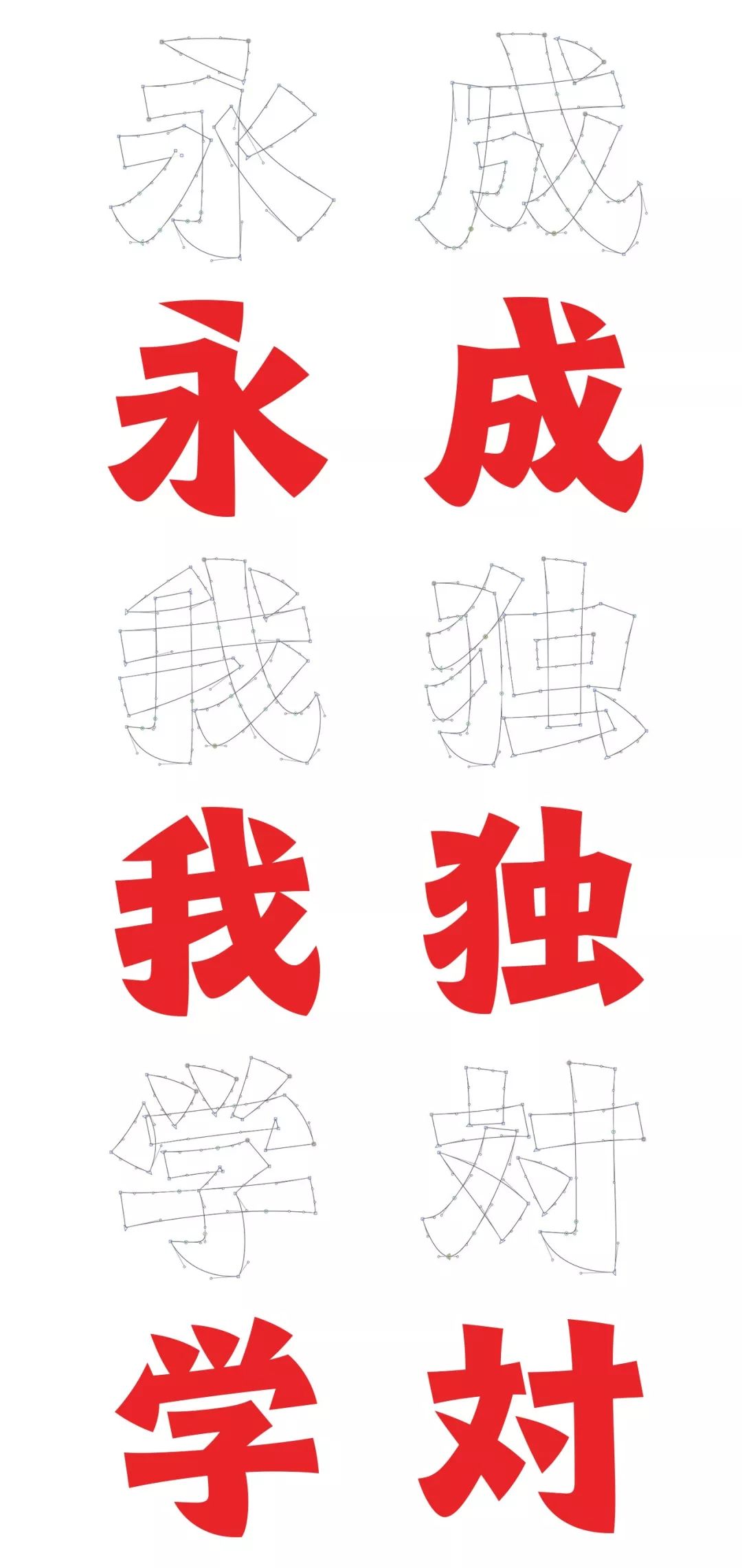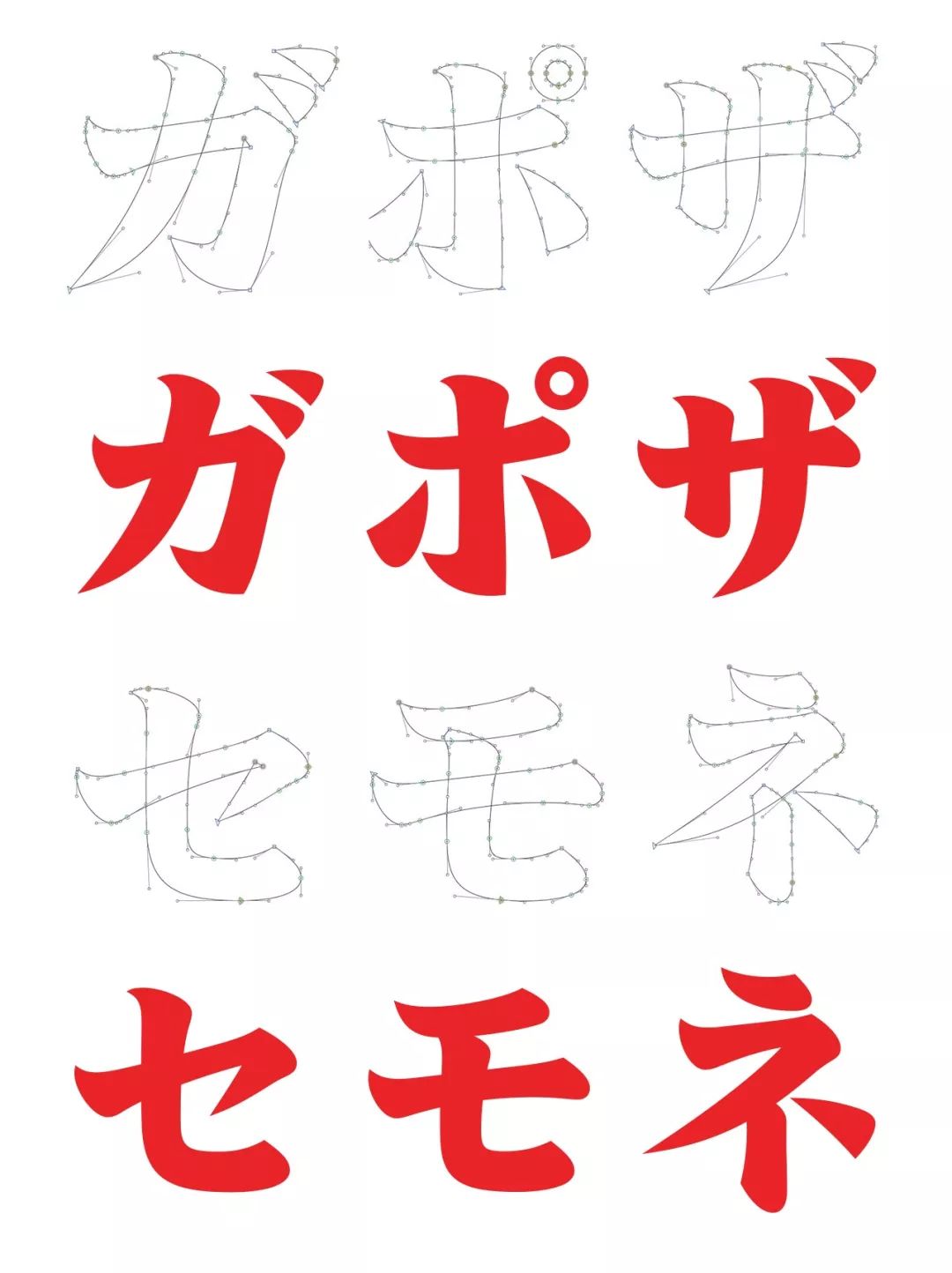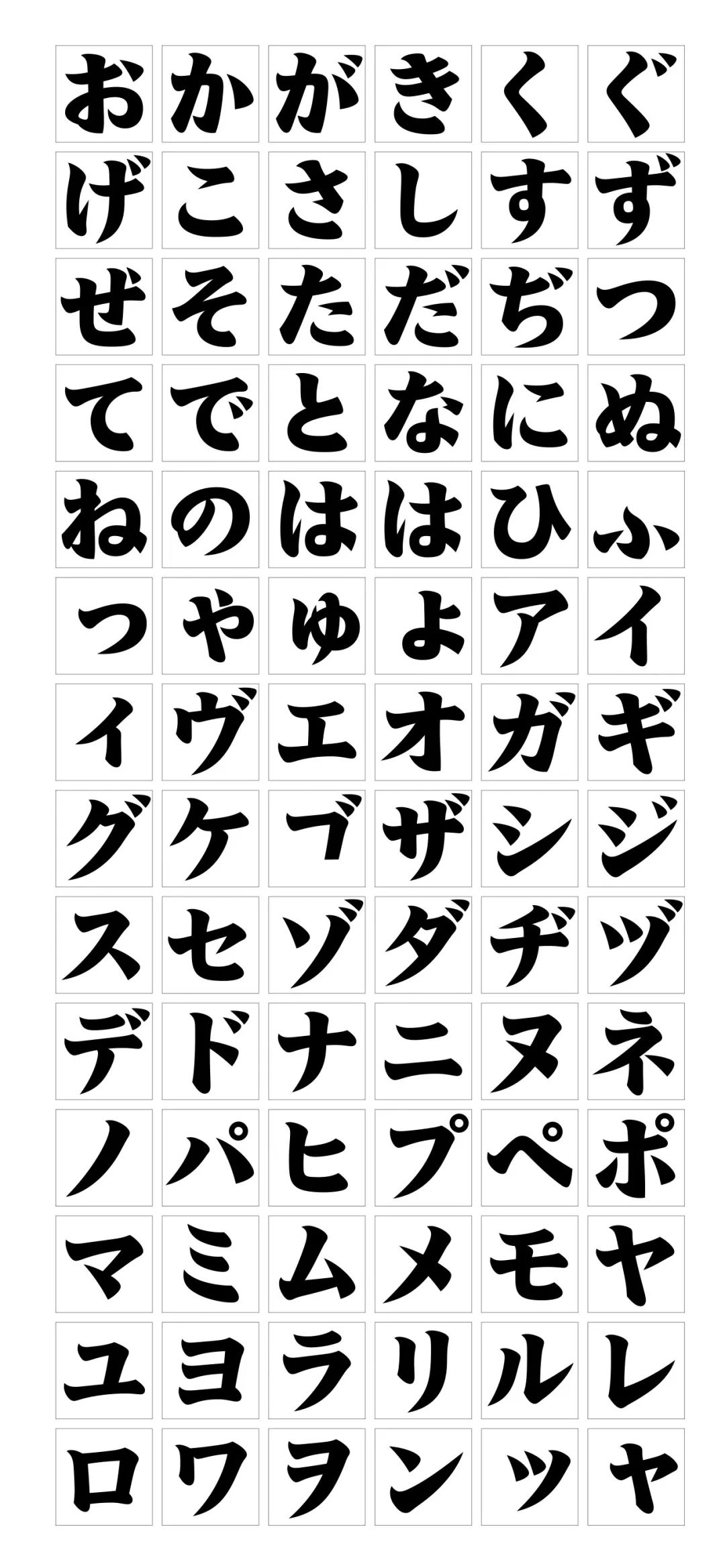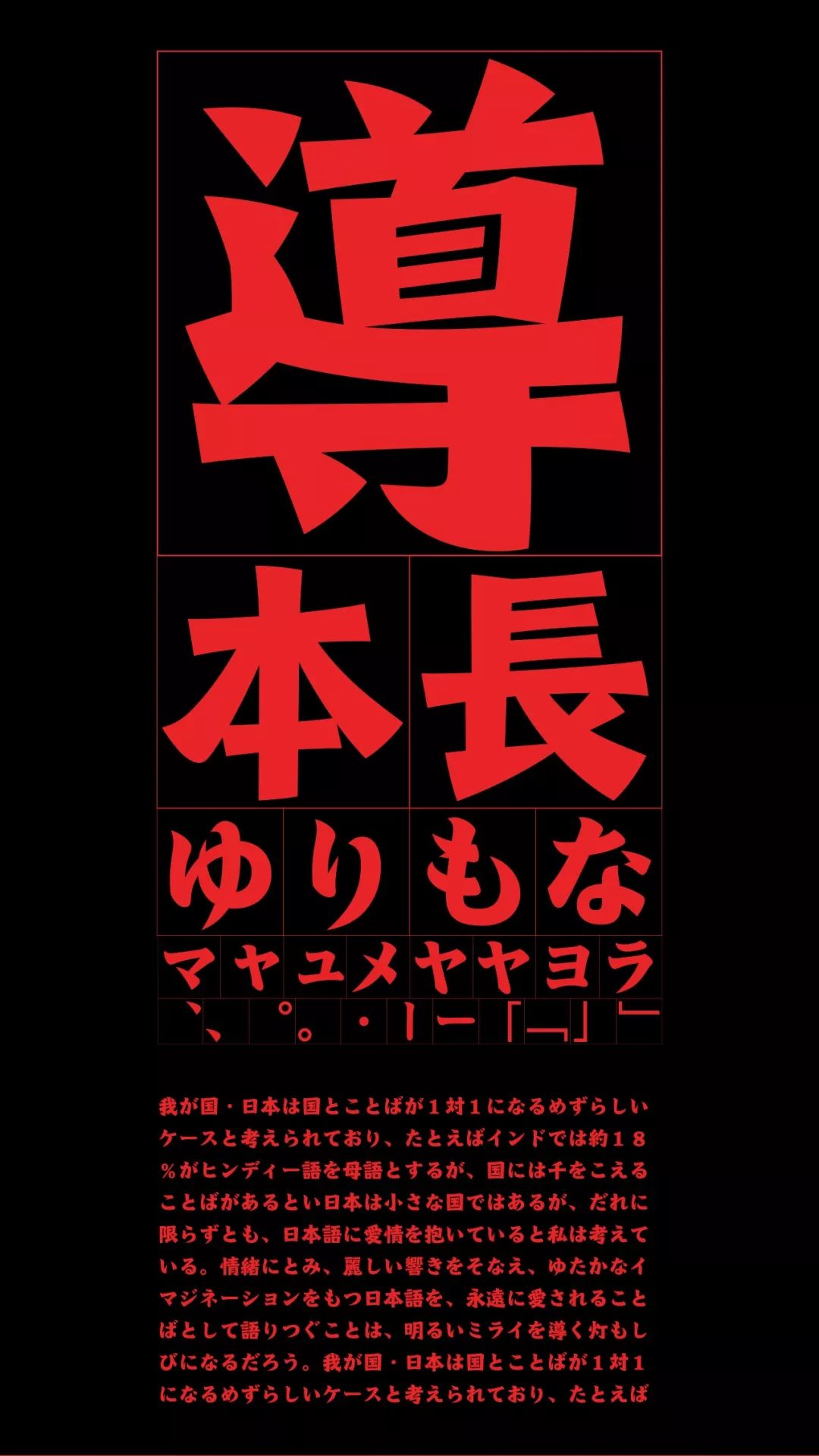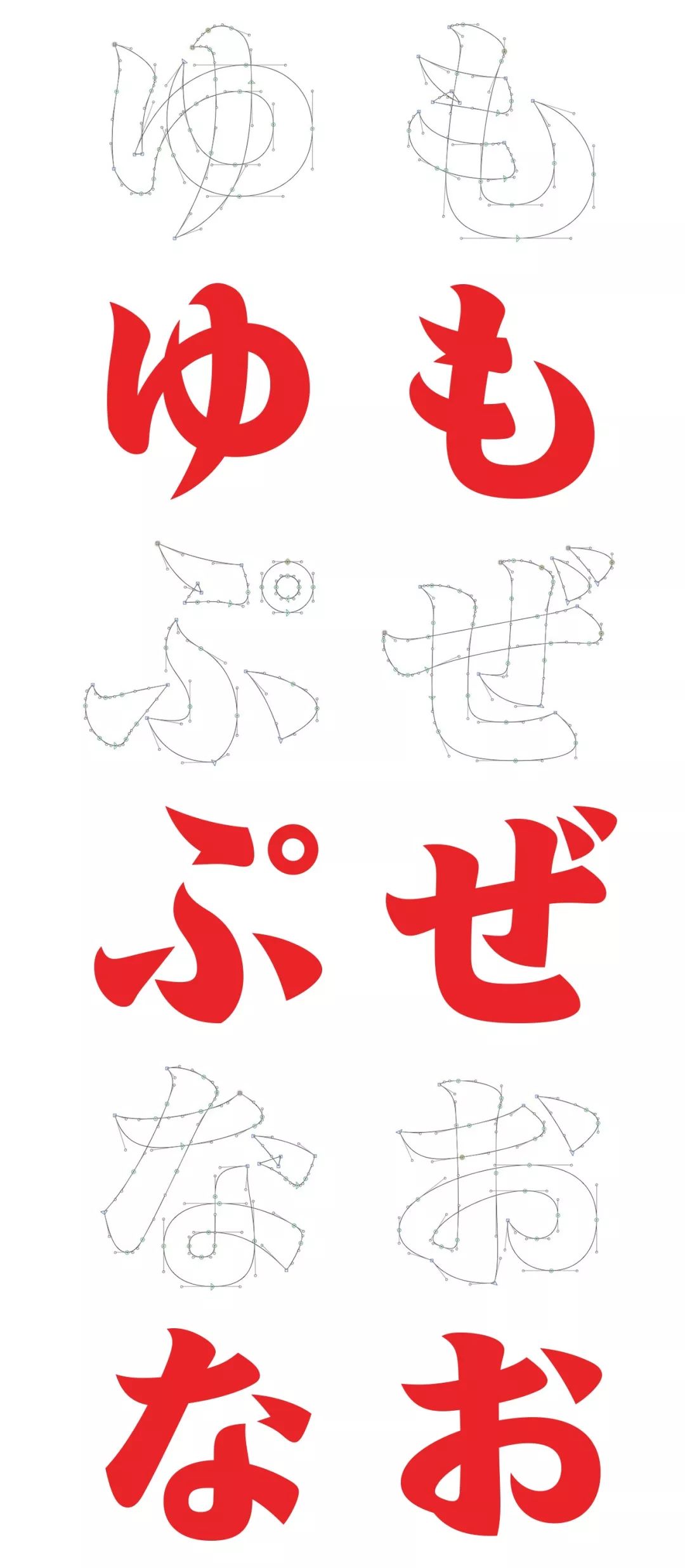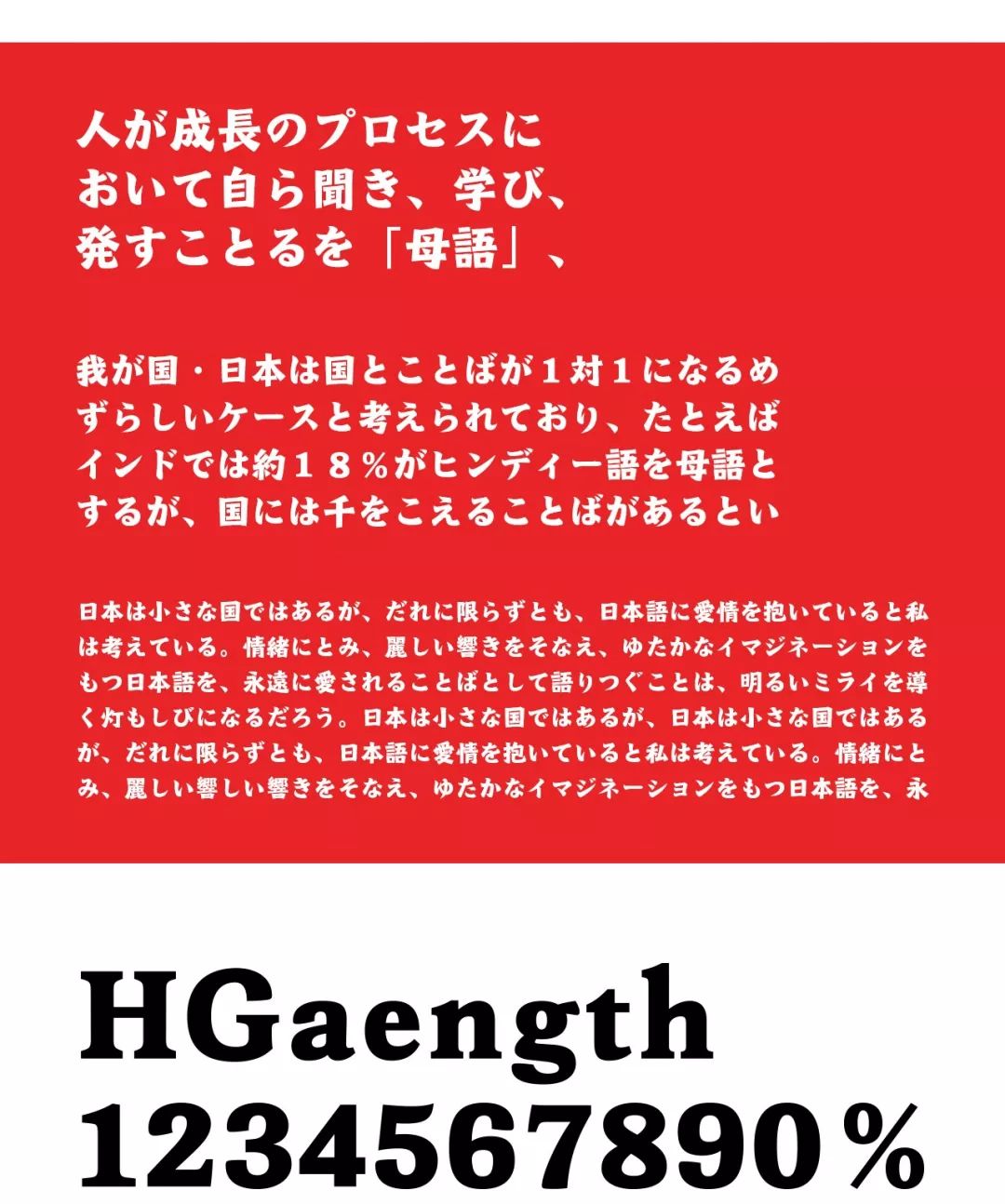
这个参加森泽字体大赛的作品,有点霸气!
今天,收到一份字体设计作品投稿。
作者是文弓随。
这是他参加日本森泽字体大赛的拙作《将军》,
希望在这里和大家展示。
可能有些人会好奇,什么是日本森泽字体大赛。我这里简单说下。日本森泽字体设计大赛(Morisawa Type Design Competition)是由日本森泽字体公司(Morisawa Inc.)创办于1984年,历经30几年,集结了世界各地具代表性的优秀评委,且持续追求展现出崭新表现力和挑战精神的字体设计。
再看回文弓随的作品。
设计说明:
提刀上阵,下马杀敌。一招一式、一板一眼、尽显阳刚。内紧外松,内圆外方。传达力量、爽利、雄健之美。师古不泥古,法前寓新,其名:《将军》 。
在字形上,
阳刚,内紧外松,内圆外方
看完文弓随作品,咱们再聊聊森泽字体设计大赛。
2019日本森泽字体设计大赛,不间断地寻找来自世界各地具有新表现力和挑战精神的字体作品。要在今年7月才发表结果。
作品参赛是免费。评委团阵容也是非常强大。包括:北川一成、鸟海修、西冢凉子、广村正彰……
森泽奖(Morisawa Award)在汉字和拉丁语两个类别征集富有创意和美学的字体设计参赛。新评审团由设计师和各个领域的和专家组成,他们将评判参赛作品。大众选择奖(People’s Choice Award)将由公众在线投票产生。
明石奖(Akashi Award)过去常常要求字体商业化。我们推出了一项新计划,每次都为比赛设定一个主题。本届主题是“可变字体variable fonts”,它是在OpenType规范中实现的。评委们将全面评估您的作品是新字体还是可转化为可变字体的作品。
最新一届的作品要7月份才有结果,那上一届2016日本森泽字体设计大赛获奖作品长什么样子呢?
汉字类,森泽奖
金奖
字体:Shimanami
设计:Junko Matsumura (日本)
银奖
字体:tsukibae
设计:Naoko Ozawa (日本)
铜奖:
字体:Natsume M / B
设计:Aki Toyoshima (日本)
荣誉奖(自左至右)
字体:Gan Kaisho   设计:Miki Ooba (日本)
字体:tgk02   设计:Yokokaku (日本)
字体:Kuretonbo   设计:Ryotaro Tada (日本)
拉丁字体类,森泽奖
金奖
字体:Vonk Regular / Italic
设计:Bart Vollebregt (荷兰)
银奖
字体:Rododendron
设计:Jitka Janeckova (捷克)
铜奖
字体:Abelha
设计:Michel Derre & Julien Priez (法国)
荣誉奖(自上至下)
字体:Edna   设计:Reymund Schroeder (德国)
字体:Newline   设计:Christian Mengelt (瑞士)
字体:TroisMille   设计:Marc Rouault (法国)
汉字类,明石奖
字体:Shimanami
设计:Junko Matsumura (日本)
拉丁字体类,明石奖
字体:Vonk Regular / Italic
设计:Bart Vollebregt (荷兰)
汉字类,人气奖
第一名(左)
字体:Madori font
设计:Sayaka Takegami (Japan)
第二名(二)
字体:Ruitai
设计:Chung Lieh Yang (台湾)
拉丁字体类,人气奖
第一名
字体:Legilux
设计:Antonia Cornelius (德国)
第二名
字体:Untitled
设计:Desmond Wong (美国)
有没有中国人在该大赛获过奖包括或者作品长什么样呢?我今天去搜集了一下,一起看看。
第一张就很威了:森泽奖获奖字体:徐明体。来自中国第一代字体设计师——徐学成老师的作品,具体获奖年份查不到。
第二个获奖作品《铁筋隶书》,来自中国著名字体设计师朱志伟先生。曾任方正字库字体开发总监,方正集团高级技术专家。《铁筋隶书》获得1999年日本森泽字体评审委员奖 。
最后,祝文弓随参加日本森泽字体大赛的拙作《将军》能得到他想要的结果!